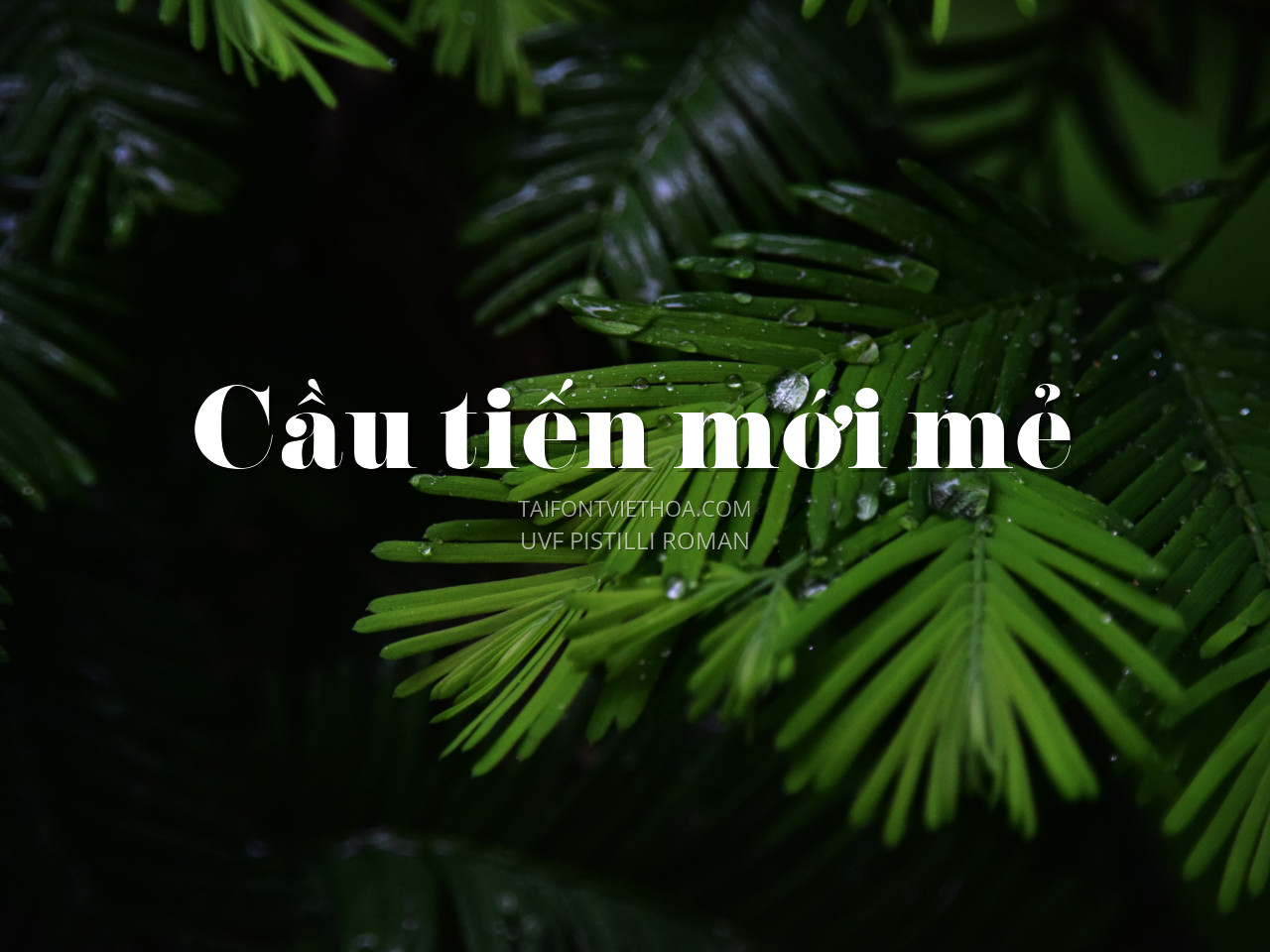
Giới thiệu về font UVF Pistilli
UVF Pistilli là một kiểu chữ serif cao cấp, nổi bật với các đường nét thanh mảnh kết hợp cùng các phần gạch chân (serif) dày bản và hiện đại. Font lấy cảm hứng từ phong cách typographic cổ điển Ý, đặc biệt là tinh thần nghệ thuật từ thập niên 60, thường gắn với các ấn phẩm thời trang và thiết kế sang trọng. Tên gọi “Pistilli” có liên quan đến Herb Lubalin và các nhà thiết kế Mỹ, từng sử dụng trong các thương hiệu thời trang lừng danh. Font hỗ trợ hơn 200 ngôn ngữ quốc tế, bao gồm cả tiếng Việt với đầy đủ dấu và ký tự đặc trưng.
Đặc điểm thiết kế và khả năng ứng dụng của UVF Pistilli
UVF Pistilli mang đậm phong cách Didone, thể hiện rõ qua độ tương phản mạnh giữa các nét dày và mảnh, tạo cảm giác mạnh mẽ và trang trọng. Đặc điểm dễ nhận biết là các chữ cái có hình dạng cao và thanh thoát, trong khi phần chân chữ được xử lý dày bản, giúp font trở thành điểm nhấn thị giác cực kỳ nổi bật. Ngoài ra, bộ font còn tích hợp nhiều ligatures và ký tự thay thế stylistic, giúp tăng tính linh hoạt cho thiết kế.
Font rất phù hợp với các ứng dụng trong thiết kế nhận diện thương hiệu thời trang, bao bì mỹ phẩm, bìa tạp chí, sách nghệ thuật và thiết kế website sang trọng. Ngành nghề phù hợp bao gồm: thời trang cao cấp, làm đẹp, kiến trúc, thiết kế sáng tạo, quảng cáo và xuất bản.